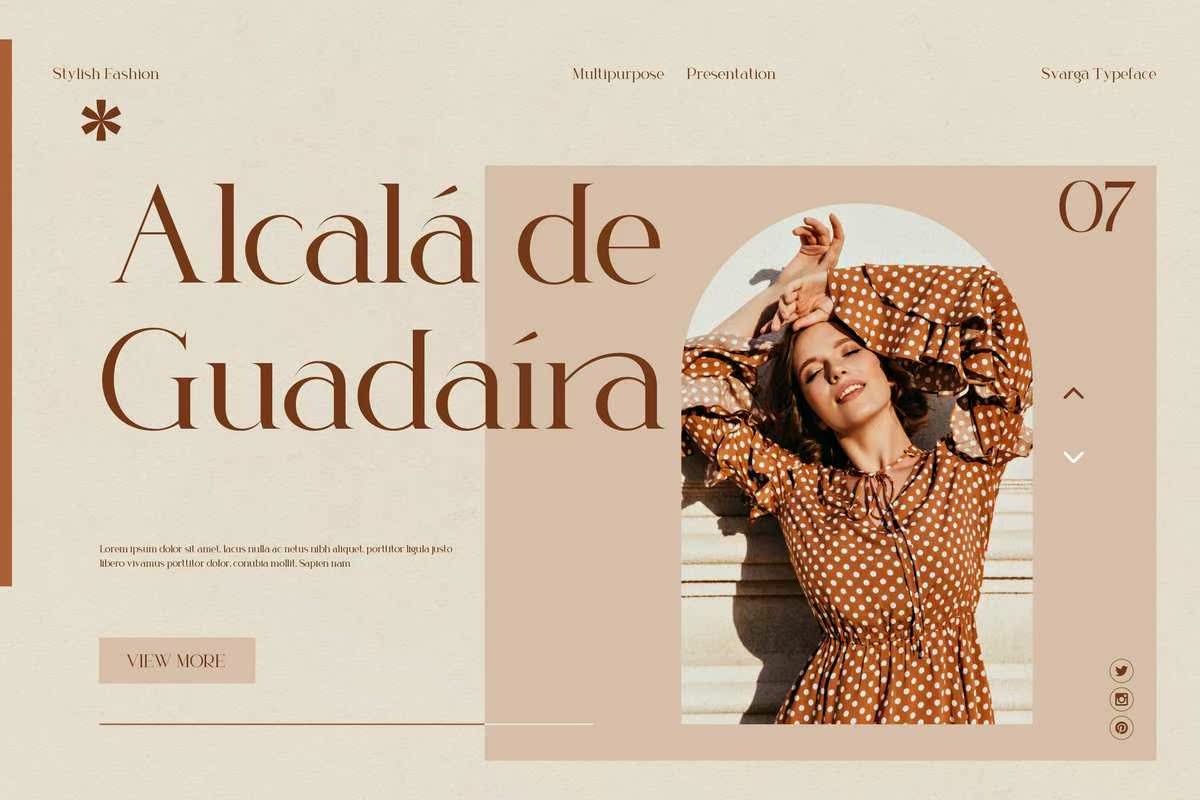
介绍全新的“Svarga”,优雅时尚的字体,具有独特、经典和风格。Svarga字体是经典和经典的字体–这是一款现代和怀旧的字体,适用于徽标、杂志、社交媒体。已准备就绪,可用于下一次设计!对于那些需要您的设计具有传奇性、时尚性、古典性、时尚性和现代性的人来说,这款Font是为您打造的!介绍全新的“Svarga”,优雅时尚的字体,具有独特、经典和风格。Svarga字体是经典和经典的字体–这是一款现代和怀旧的字体,适用于徽标、杂志、社交媒体。已准备就绪,可用于下一次设计!对于那些需要您的设计具有传奇性、时尚性、古典性、时尚性和现代性的人来说,这款Font是为您打造的!